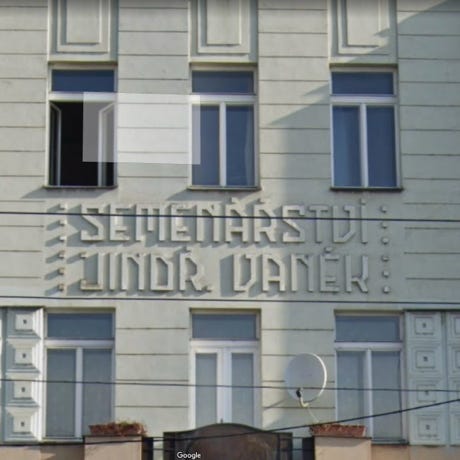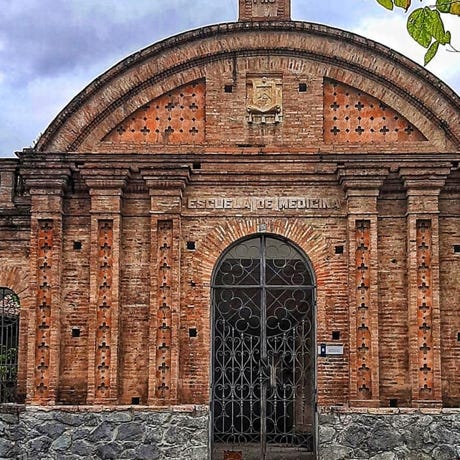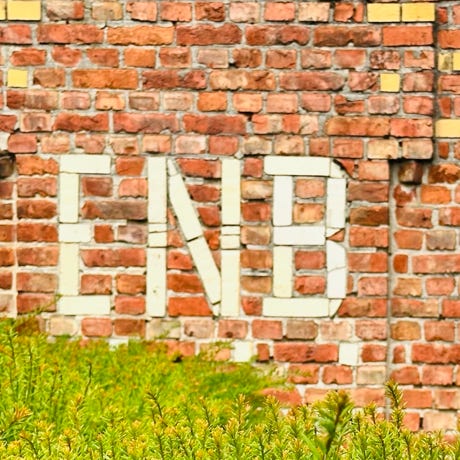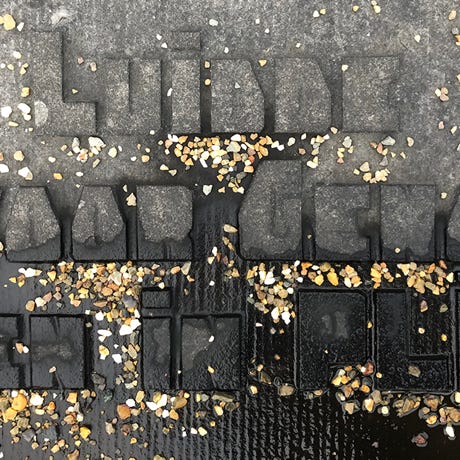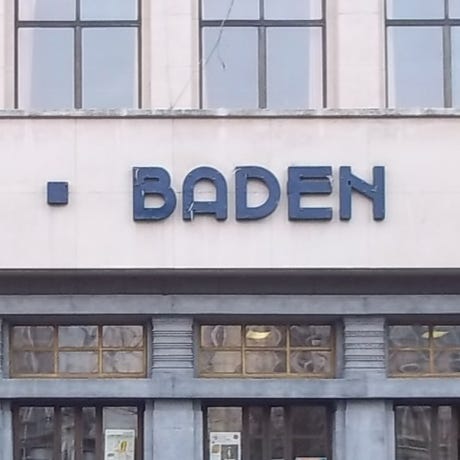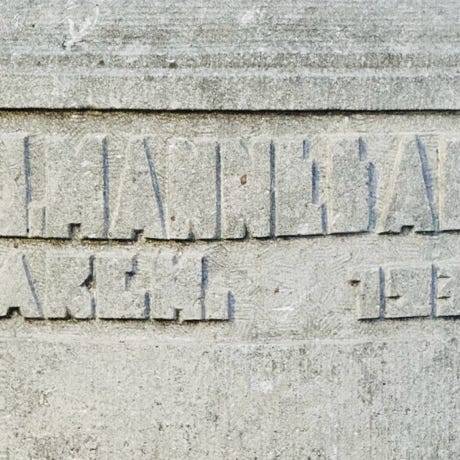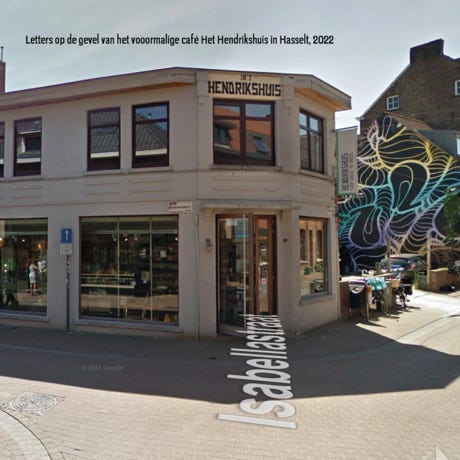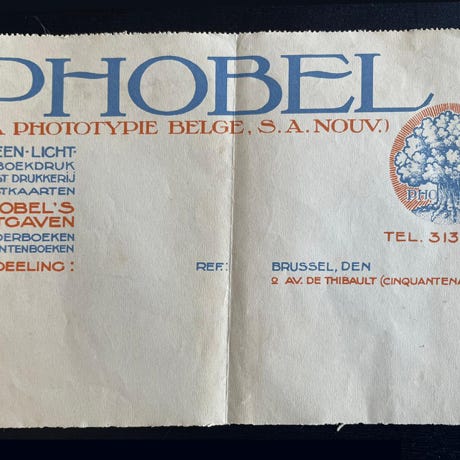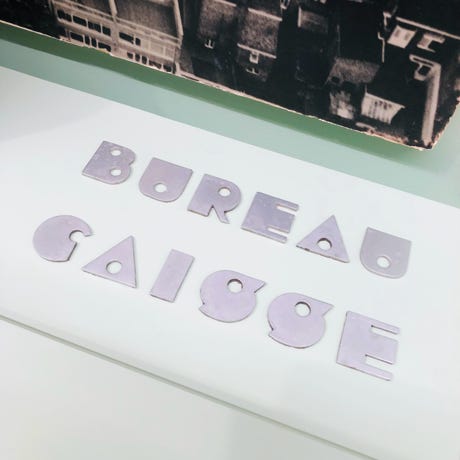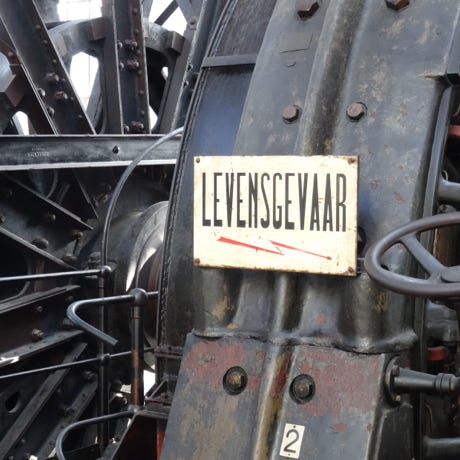
Wij van FONTRESCUE gaan op zoek naar oude letters op gebouwen, grafstenen, machines,..... Letters soms ontworpen door bouwmeesters, maar meestal is de auteur onbekend.
Voor ze verdwijnen willen we ze redden door ze te digitaliseren en door ze aan te vullen tot een volwaardig bruikbaar lettertype.
Dat is deel één van onze missie.
Deel twee is het toepassen van de letters in nieuwe projecten en het terug tot leven brengen met hedendaagse technieken.
We at FONTRESCUE search for old letters on buildings, tombstones, machines,..... Letters sometimes designed by master builders, but usually the author is unknown.
Before they disappear, we want to save them by digitising them and supplementing them into a fully usable typeface.
That is part one of our mission.
Part two is applying the letters in new projects and bringing them back to life with contemporary techniques.